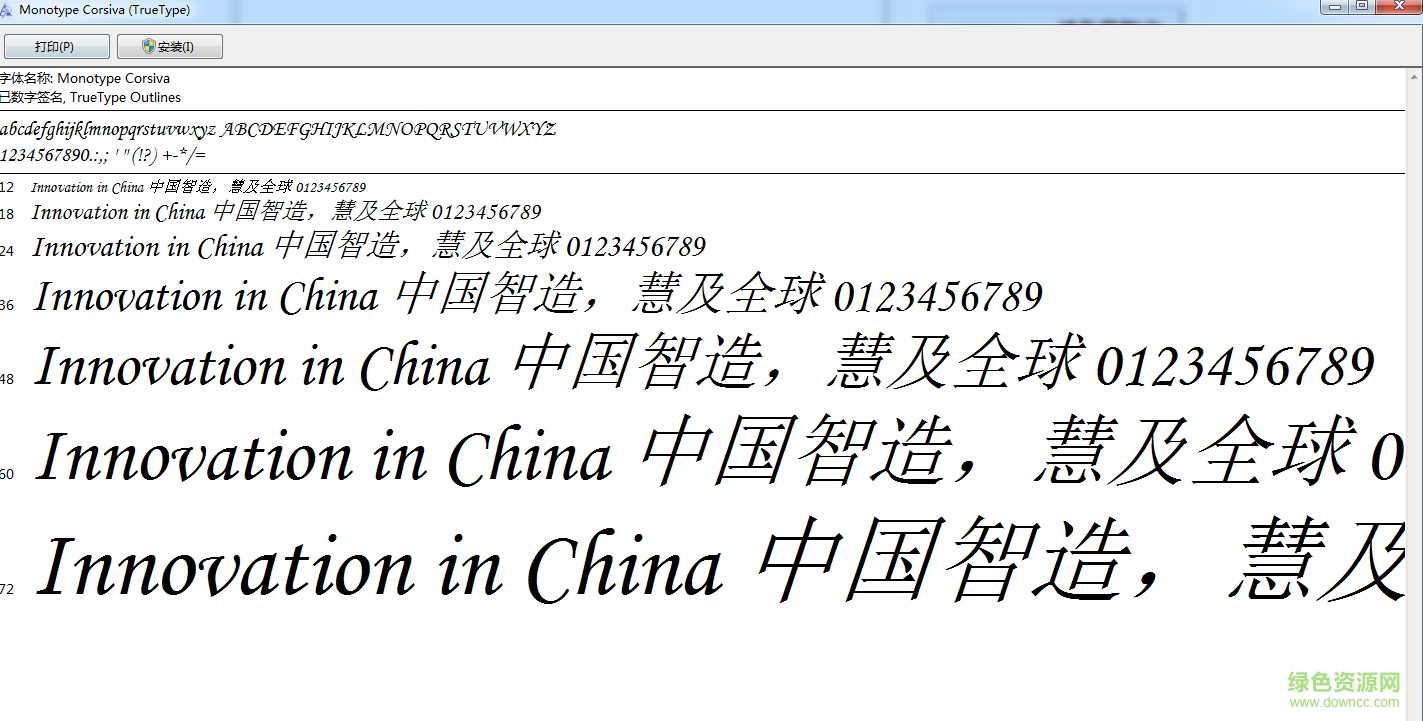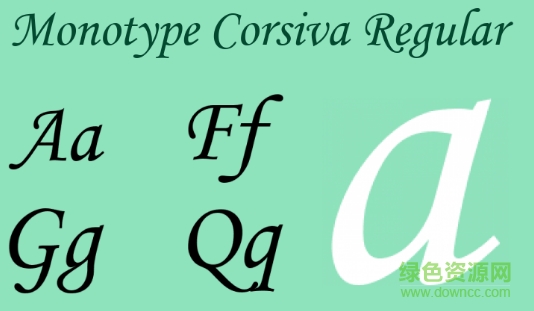
monotypecorsiva字體
Monotype字型介紹
Monotype 字型圖書館包含了全球最多—超過7000種字型,其中最知名的字型有:Baskerville, Bell, Bembo, Centaur, Garamond, Gill Sans, Plantin, Rockwell, Walbaum以及也許是在字型界中最眾所周知的Times New Roman。
monotype corsiva字體
monotype corsiva字體特點(diǎn)
起筆如蝌蚪形的頓點(diǎn)、螺螄轉(zhuǎn)似的小鉤,配以修長(zhǎng)的字形,如少女般婷婷玉立,裊娜動(dòng)人,美觀而不落俗套!